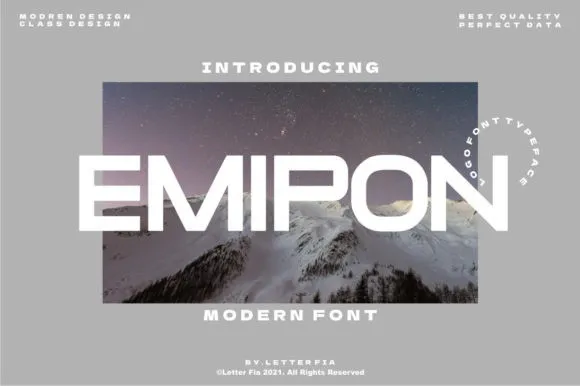
A Emipon Font é uma excelente escolha para aqueles que buscam uma nova maneira de dar vida às suas criações digitais, oferecendo um visual único e moderno. Desenvolvida pela Letter Fia, essa fonte do tipo display apresenta linhas retas com contraste notável e traços sem serif pesados. Suavemente despojada, a Emipon é perfeita para usar em elementos visuais que buscam chamar atenção ou criar um impacto visual forte. Com seus traços leves e modernos, essa fonte se destaca em qualquer projeto de design gráfico, seja ele digital ou impresso. Engajante e versátil, a Emipon é uma ótima adição para quem busca uma fonte do tipo display de alta qualidade que irá inspirar seus projetos. Experimente e descubra as inúmeras possibilidades que essa font oferece.